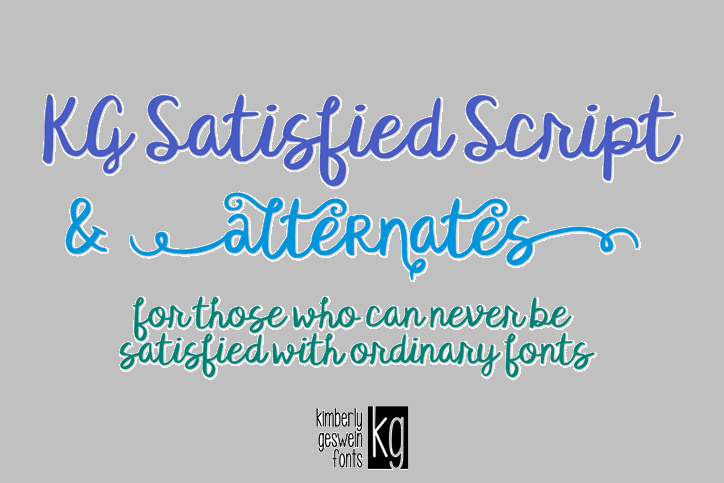
KG Satisfied Script Font – Download Grátis
A fonte KG Satisfied Script Font é uma herança do mundo das artes orientais e traz aos artistas digitais brasileiros uma opção irresistível para criar texturas encantadoras e elegantes. Criada pelo talentoso designer Hamilton, esta fonte de calligrafia tem nuances únicas que a tornam não apenas versátil mas também uma paixão para aqueles que desejam dar um toque refinado em seus projetos pessoais ou comerciais. Ideal para adicionar um toque de sofisticação à sua identidade visual, seja no branding da sua marca ou decorando as páginas dos seus anúncios publicitários, a KG Satisfied Script Font é perfeita para criar texturas suaves e expressivas. Ela é uma fonte convidativa que se mistura harmoniosamente com outras fontes serifadas e não-serifadas, permitindo aos criativos brasileiros explorarem novas maneiras de expressar suas ideias em design. Para quem deseja incorporá-la ao seu trabalho comercial, a Kimberly Geswein disponibiliza uma licença especial no site http://kimberlygeswein.com. Não hesite em explorar as possibilidades criativas da KG Satisfied Script Font e faça sua marca se destacar no mercado brasileiro, seja com design de sites pessoais ou profissionais, logomarcas, anúncios digitais, embalagens ou qualquer outro projeto visual que exija uma fonte chamativa e sofisticada.